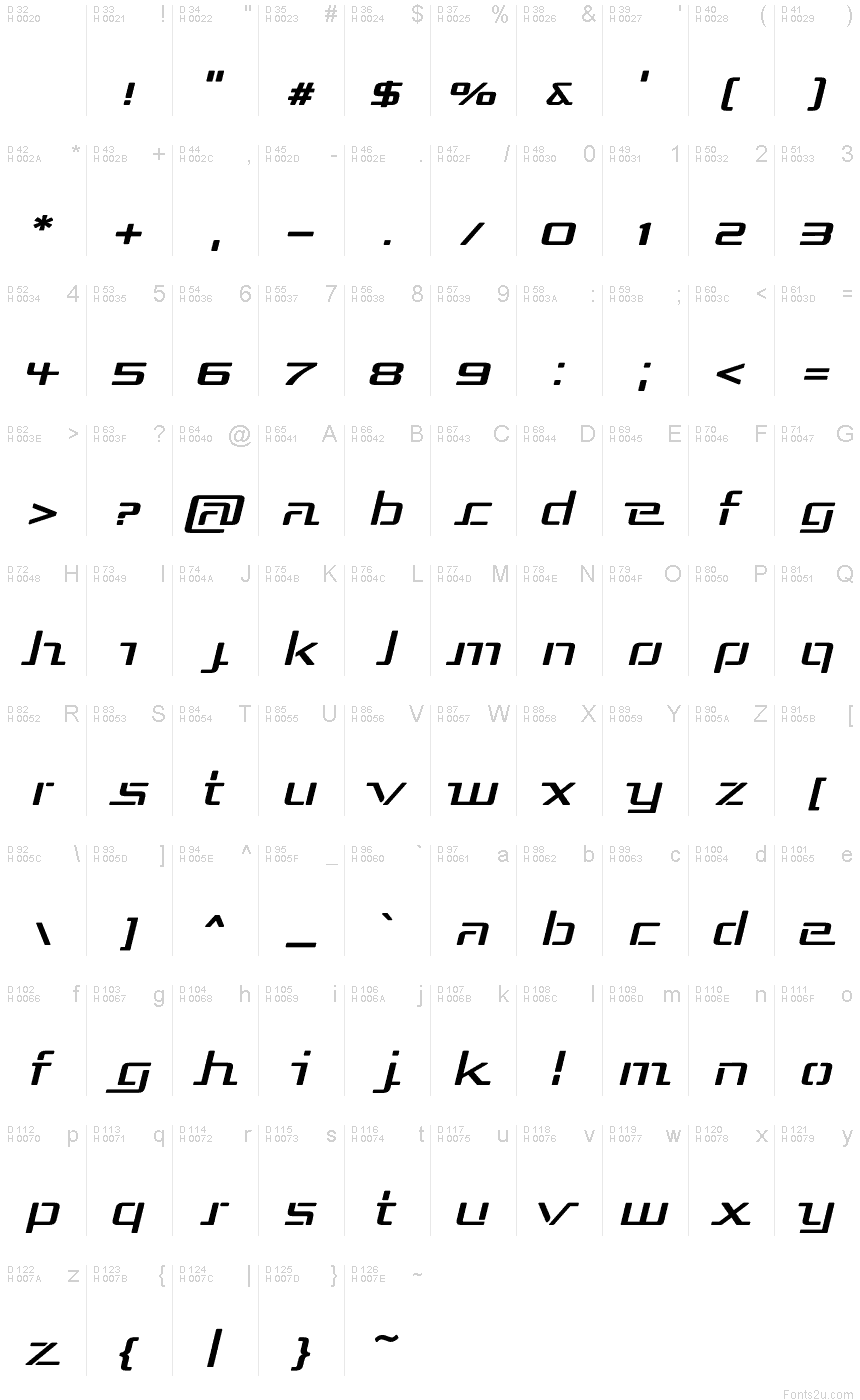
Republika III Exp Italic
Republika III Exp Italic di Apostrophe è un font display gratuito e futuristico dal ritmo techno elegante. Le lettere hanno un'inclinazione decisa e si muovono su tratti rettangolari arrotondati, alternando curve morbide a tagli netti: un alfabeto dal look rapido e sintetico, perfetto per il branding digitale contemporaneo.
Si adatta perfettamente a grafiche musicali, titoli di giochi, poster, copertine di album e bozzetti di loghi dove serve un font gratuito che trasmetta movimento anziché decorazione. Poiché le maiuscole richiamano un sistema connesso di binari e pannelli, è ideale anche per etichette di interfacce, monogrammi e titoli di copertina che cercano quel look compatto fantascientifico.